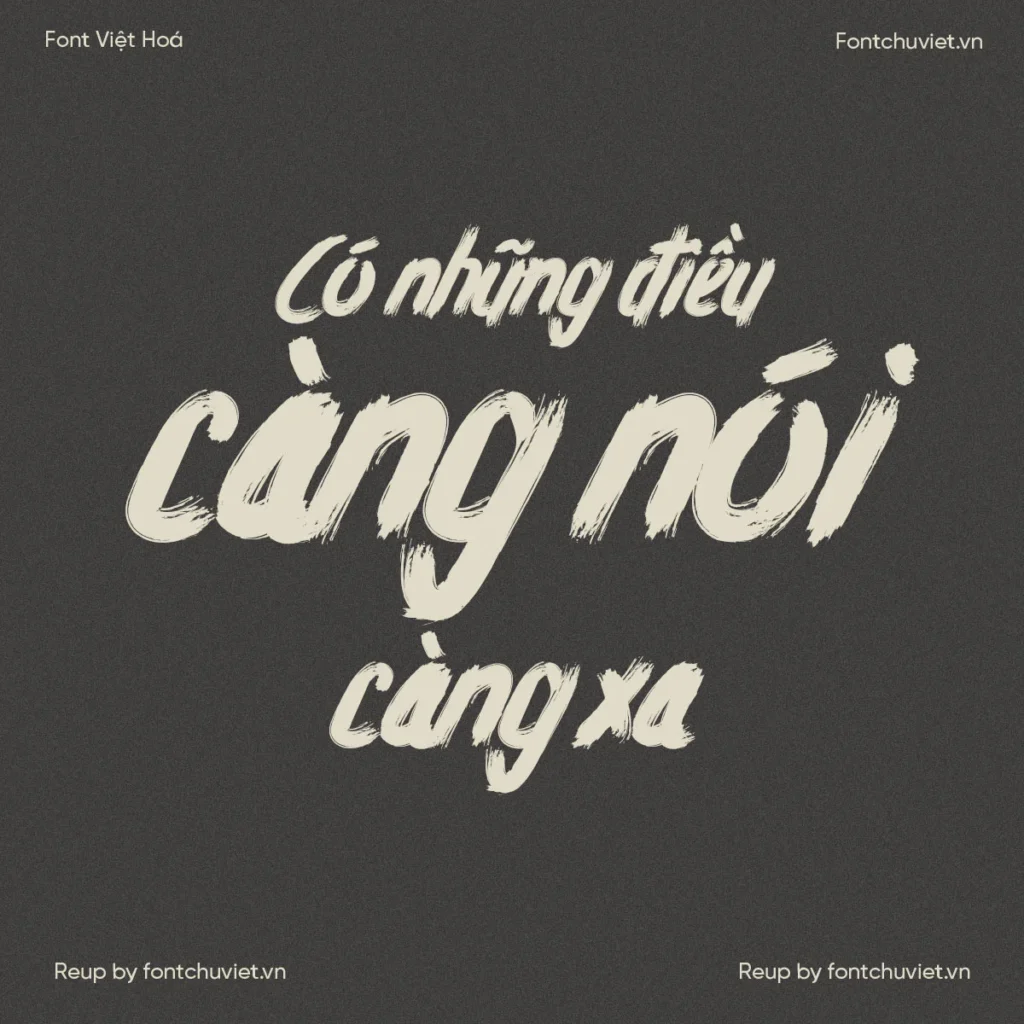
Font VL Atorak Typeface – Font Việt hoá là một trong những font chữ phổ biến nhất hiện nay. Với thiết kế độc đáo và sang trọng, font này đã trở thành sự lựa chọn hàng đầu cho nhiều nhà thiết kế. Font VL Atorak Typeface – Font Việt hoá không chỉ đẹp mà còn rất dễ đọc, giúp người dùng có thể dễ dàng đọc và hiểu nội dung.
Font VL Atorak Typeface – Font Việt hoá: Ưu Điểm Và Nhược Điểm
Font VL Atorak Typeface – Font Việt hoá có nhiều ưu điểm, bao gồm thiết kế đẹp, dễ đọc và sự linh hoạt trong việc sử dụng. Tuy nhiên, font này cũng có một số nhược điểm, như kích thước lớn và không phù hợp với tất cả các loại thiết kế.
Cách Sử Dụng Font VL Atorak Typeface – Font Việt hoá Hiệu Quả
Cách Chọn Font Phù Hợp
Để sử dụng Font VL Atorak Typeface – Font Việt hoá hiệu quả, bạn cần chọn font phù hợp với thiết kế của mình. Hãy xem xét kích thước, màu sắc và phong cách của font để đảm bảo rằng nó phù hợp với nội dung và thiết kế.
Cách Tối Ưu Hóa Font
Bạn cũng có thể tối ưu hóa Font VL Atorak Typeface – Font Việt hoá bằng cách điều chỉnh kích thước, màu sắc và phong cách. Điều này sẽ giúp font trở nên đẹp và hiệu quả hơn trong việc truyền tải nội dung.
Ứng Dụng Của Font VL Atorak Typeface – Font Việt hoá
Font VL Atorak Typeface – Font Việt hoá có nhiều ứng dụng trong việc thiết kế. Bạn có thể sử dụng font này để tạo ra các thiết kế đẹp và sang trọng, từ các trang web đến các tài liệu in ấn.
Lợi Ích Của Font VL Atorak Typeface – Font Việt hoá
Font VL Atorak Typeface – Font Việt hoá mang lại nhiều lợi ích cho người dùng. Font này không chỉ đẹp mà còn rất dễ đọc, giúp người dùng có thể dễ dàng đọc và hiểu nội dung.
Tóm lại, Font VL Atorak Typeface – Font Việt hoá là một trong những font chữ phổ biến nhất hiện nay. Với thiết kế độc đáo và sang trọng, font này đã trở thành sự lựa chọn hàng đầu cho nhiều nhà thiết kế. Nếu bạn đang tìm kiếm một font chữ đẹp và hiệu quả, hãy thử Font VL Atorak Typeface – Font Việt hoá ngay hôm nay!